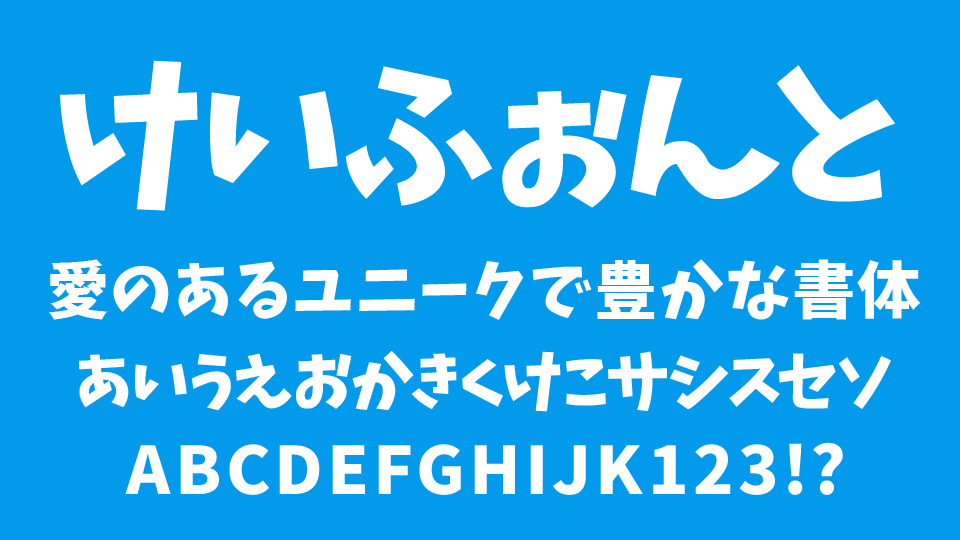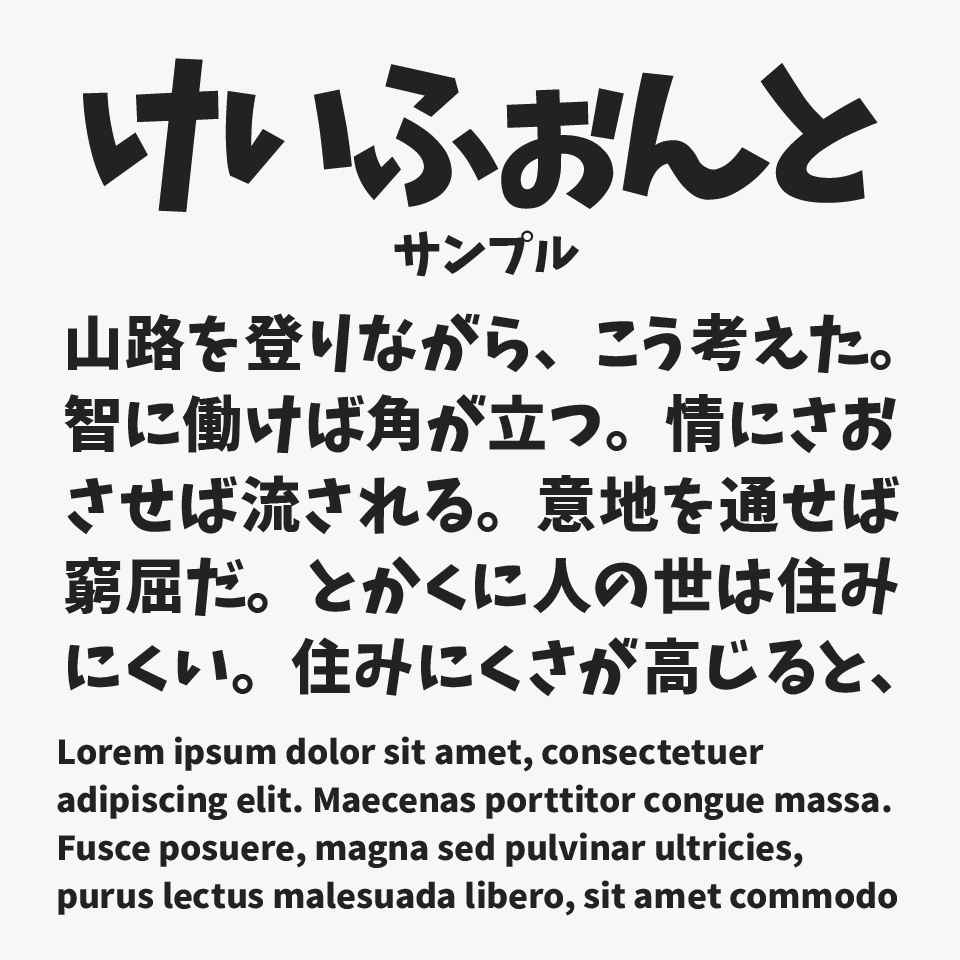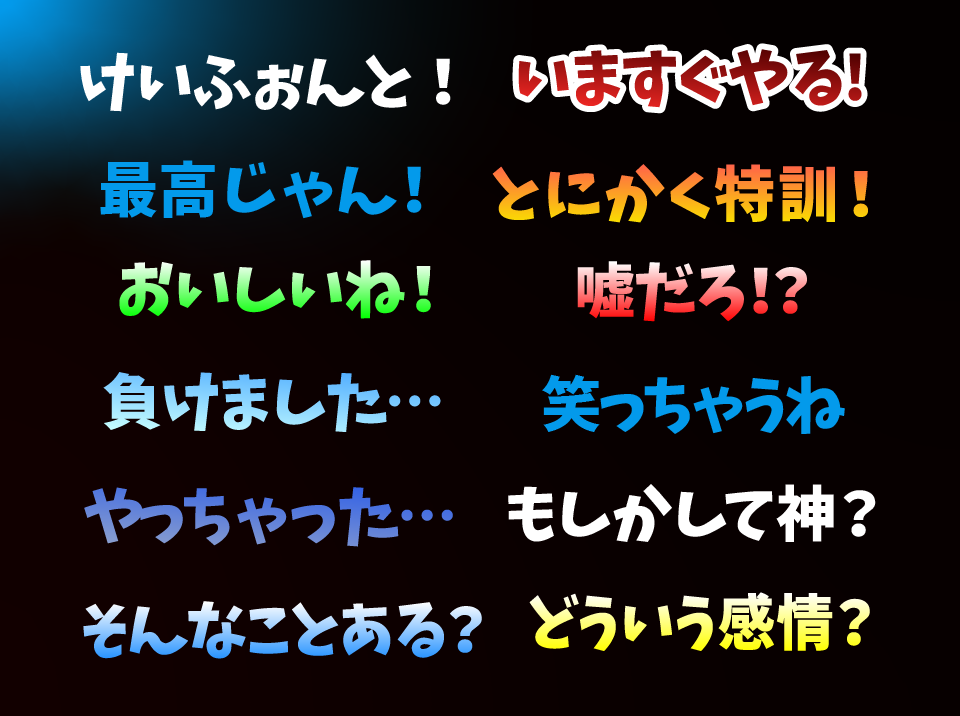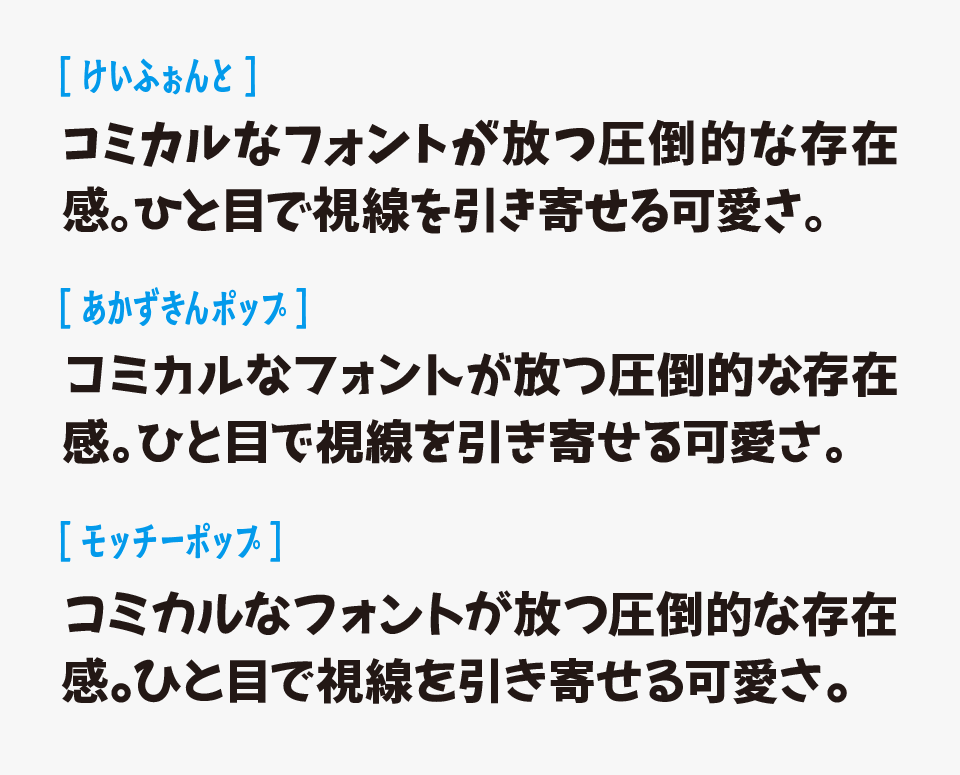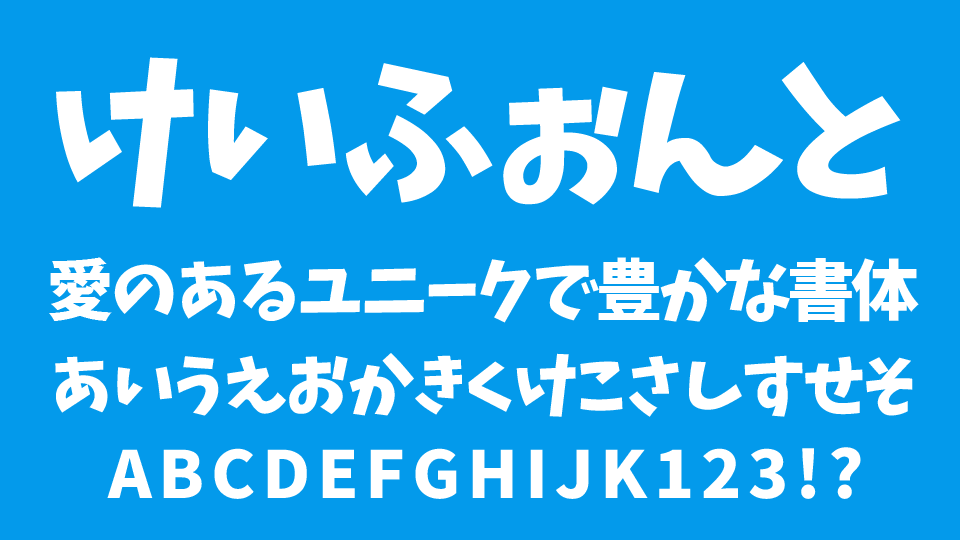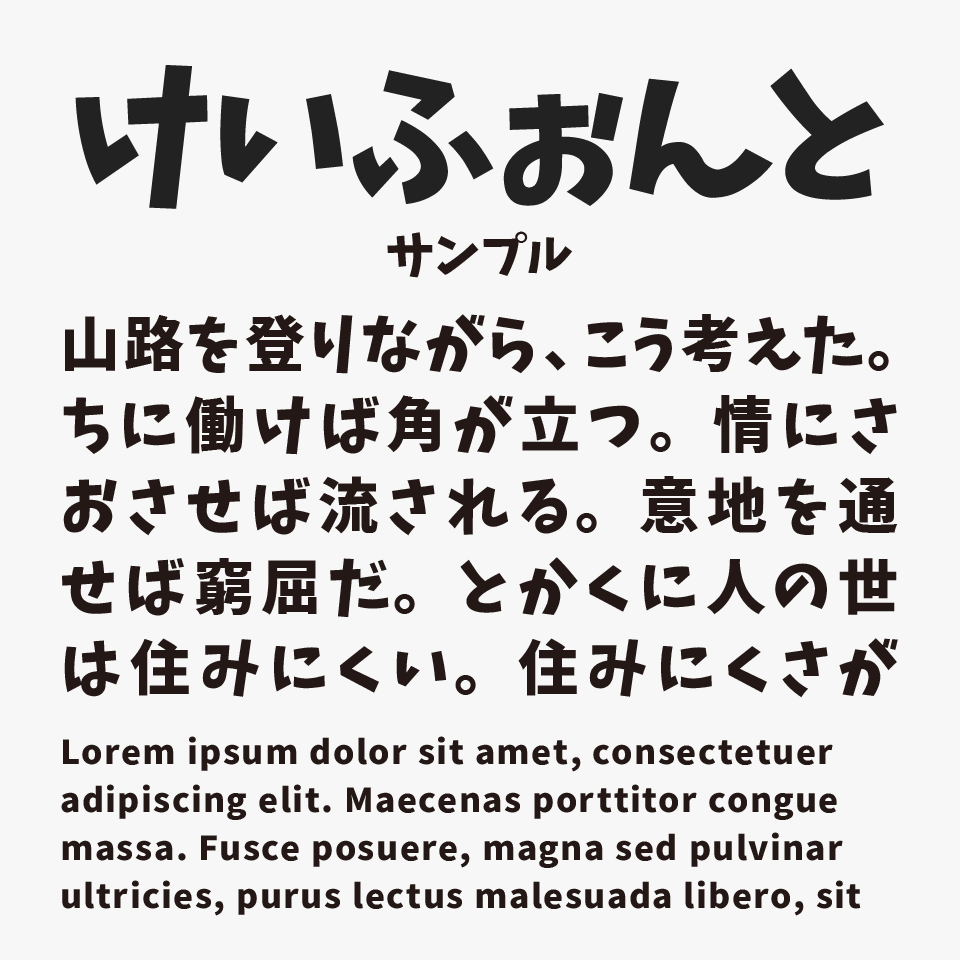
「けいふぉんと!」は、アニメ『けいおん!』のロゴタイプをヒントに制作されたデザインゴシック体フォントです。
アニメロゴに似せた可愛いフォルムが特徴で、同人誌・動画サムネイル・アイキャッチなど、可愛らしさとインパクトを求めるデザインにぴったりです。長文テロップでも視認性が高く、動画制作のサムネイル・アイキャッチ・テロップデザインで人気のフォントです。
なお、実際の『けいおん!』ロゴのトレースではないため、「け」「い」「お」「ん」の4文字も実物とは異なります。
ロゴのような数文字を使ったデザインはもちろん、長文でも「けいふぉんと!」ならではの可愛らしさと読みやすさがしっかり感じられるフォントです。特に、ひらがな・カタカナのかな文字がとても魅力的で、やわらかく親しみやすい雰囲気をつくってくれます。
文字のリズム感や丸みのあるシルエットが心地よく、ポップなデザインとの相性も抜群です。動画制作では、テロップやサムネイル、アイキャッチなどにもよく使われており、かわいさと視認性を両立したフォントとして人気のあるフォントです。
ほかのコミカルなフォントを比較してみると、「けいフォント」は手書きっぽさのある直線がラフな雰囲気がとっても可愛いですね。コミカル系フォントでも、それぞれ丸みの強さや勢い、クセの出方が異なるので、場面にあわせて使い分けても面白かもしれません。(あかずきんポップ/モッチーポップと比較)
収録文字は、オリジナル制作されているひらがな・カタカナ以外はオープンソースフォント「源ノ角ゴシック」が使用されています。源ノ角ゴシックがベースとなっているため、漢字収録数が多いのも嬉しいフォントです。